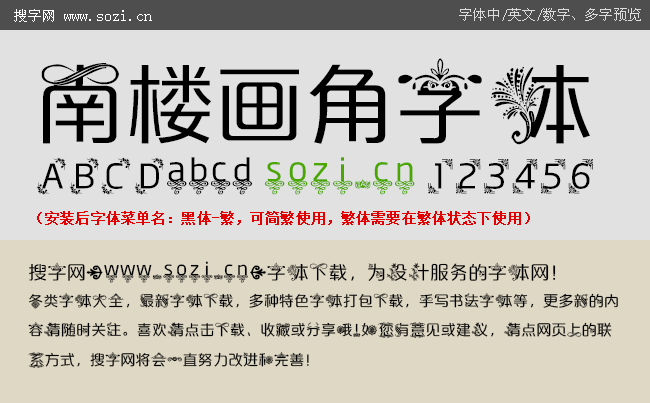
南樓畫角字體
搜字網(wǎng)給大家提供一款南樓畫角字體手機(jī)中文字體下載。這款手機(jī)字體是以藝術(shù)黑體字體為原形,筆畫間嵌入了漂亮的花紋圖案。在保持字體清晰端正的風(fēng)格同時,卡通味也特別濃,是一款非?蓯鄣目ㄍㄗ煮w,特別適合喜歡手機(jī)字體個性一些的朋友在手機(jī)上安裝使用。